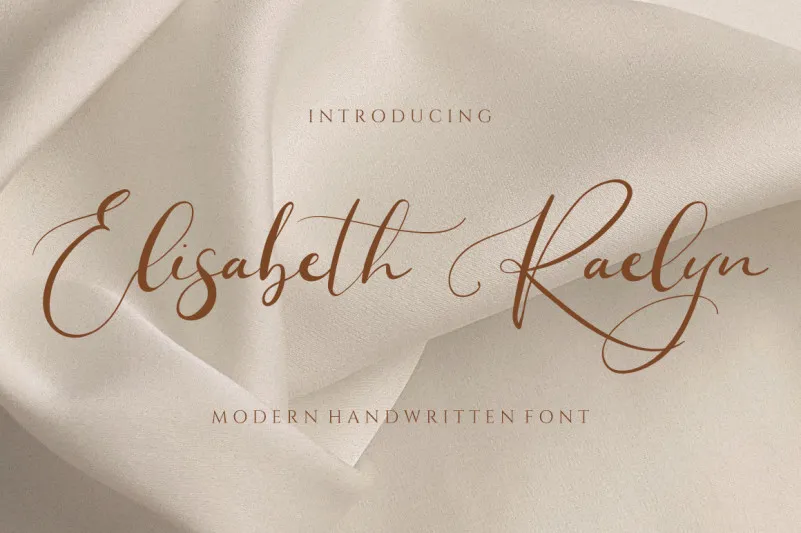
Elisabeth Raelyn Font – Fonte Grátis
Elisabeth Raelyn Font
A Elisabeth Raelyn Font é uma deliciosa mistura de escrita elegante e handwritten, ideal para projetos que buscam dar um toque de luxo a qualquer projeto. Esta fonte moderna e autêntica é perfeita tanto para aplicar em logos, assinaturas ou embalagens de produtos quanto para criar convites de casamento ou até mesmo materiais promocionais. Suas linhas suaves e sua forma única criam um impacto atraente que dará aos seus projetos uma sensação de sofisticação e elegância. O design da Elisabeth Raelyn Font é perfeito para quem busca uma mistura cuidadosa entre a escrita tradicional e a modernidade, proporcionando um aspecto autêntico. Este estilo clássico atualizado está disponível em uma variedade de aplicações, como assinaturas, embalagens e até mesmo materiais promocionais, onde suas linhas delicadas e seu design único criam um efeito imediatamente reconhecível. Essa fonte é perfeita para quem busca algo que combine charme com modernidade. Ela não apenas adicionará uma sensação de sofisticação a qualquer projeto, mas também dará aos seus designs aquele toque especial e inovador que faz toda a diferença. Experimente essa Elisabeth Raelyn Font e veja como ela pode revolucionar suas próximas criações gráficas.